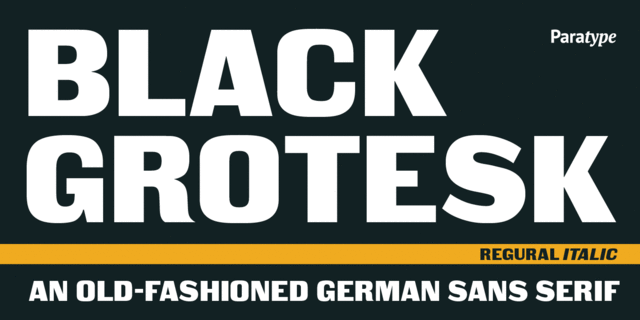
Шрифт разработан в фирме ПараТайп (ПараГраф) в 1997 (дизайнер Тагир Сафаев) на основе рисунков шрифтов Газетный черный («Дубовый») словолитного заведения О.И.Лемана (С.-Петербург, 1874) и Kompakte Grotesk фирмы Haas. Относится к группе старых немецких гротесков. Предназначен для применения в рекламе и акциденции.
Функции семейства Black GroteskПрименение в макете:
Ассоциации c семейством Black GroteskКачества и характер:
тяжелый, заметный, яркий, активный, броский, убедительный, твердый, серьезный, надежный, уверенный, сильный, устойчивый, индустриальный, крутой, амбициозный, жесткий, суровый, консервативный, настойчивый, срочный
— Возраст:
Особенности семейства Black GroteskХит десятилетия:
Хит 1910-х Хит 1920-х Близкий исторический оригинал: